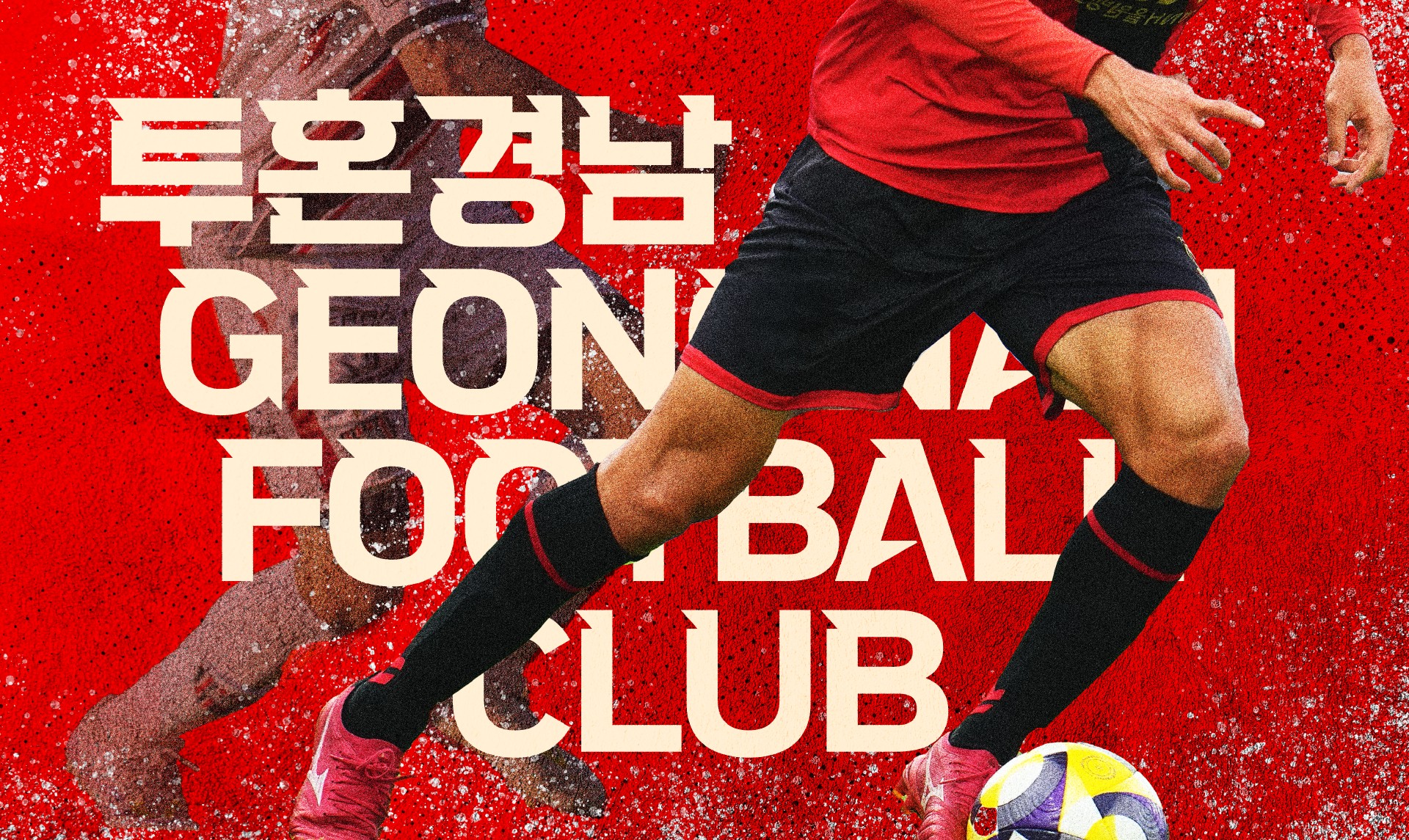
투혼경남체 — 경남FC에서 배포하는 무료 폰트입니다. 장미의 가시 같은 세리프와 단단한 골격으로, 구단의 투혼과 스포츠 감성을 담은 제목용 서체
프로축구단 경남FC가 창단 20주년을 맞아 윤디자인과 함께 만든 서체로 2026년 3월 홈 개막전에서 공개했습니다. 로고 리뉴얼과 함께 진행된 프로젝트이고 디자이너는 김미래, 김채림, 이예형입니다.
조형 설명이 인상적입니다. 제작사는 장미의 가시 같은 세리프와 단단한 골격으로 경남FC의 투혼과 정체성을 시각화했다고 밝혔습니다. 구단 상징인 사선을 기본 골격으로 삼아 강인한 인상을 냈고, 꽉 찬 모듈 설계로 무게중심을 잡았습니다.
스포츠 서체다운 배려도 들어 있습니다. 경기에서 숫자를 쓸 일이 많다 보니 폭을 좁힌 숫자 열 자를 따로 만들어 넣었습니다. 등번호나 스코어를 조판할 때 쓰라는 뜻입니다. 굵기는 Medium과 Bold, Black 세 가지이고 현대 한글 11,172자에 구단 캐릭터 딩벳까지 담았습니다. 무료로 쓸 수 있지만 수정과 재배포, 유료 판매는 금지되고 원본 형태 그대로 써야 합니다.